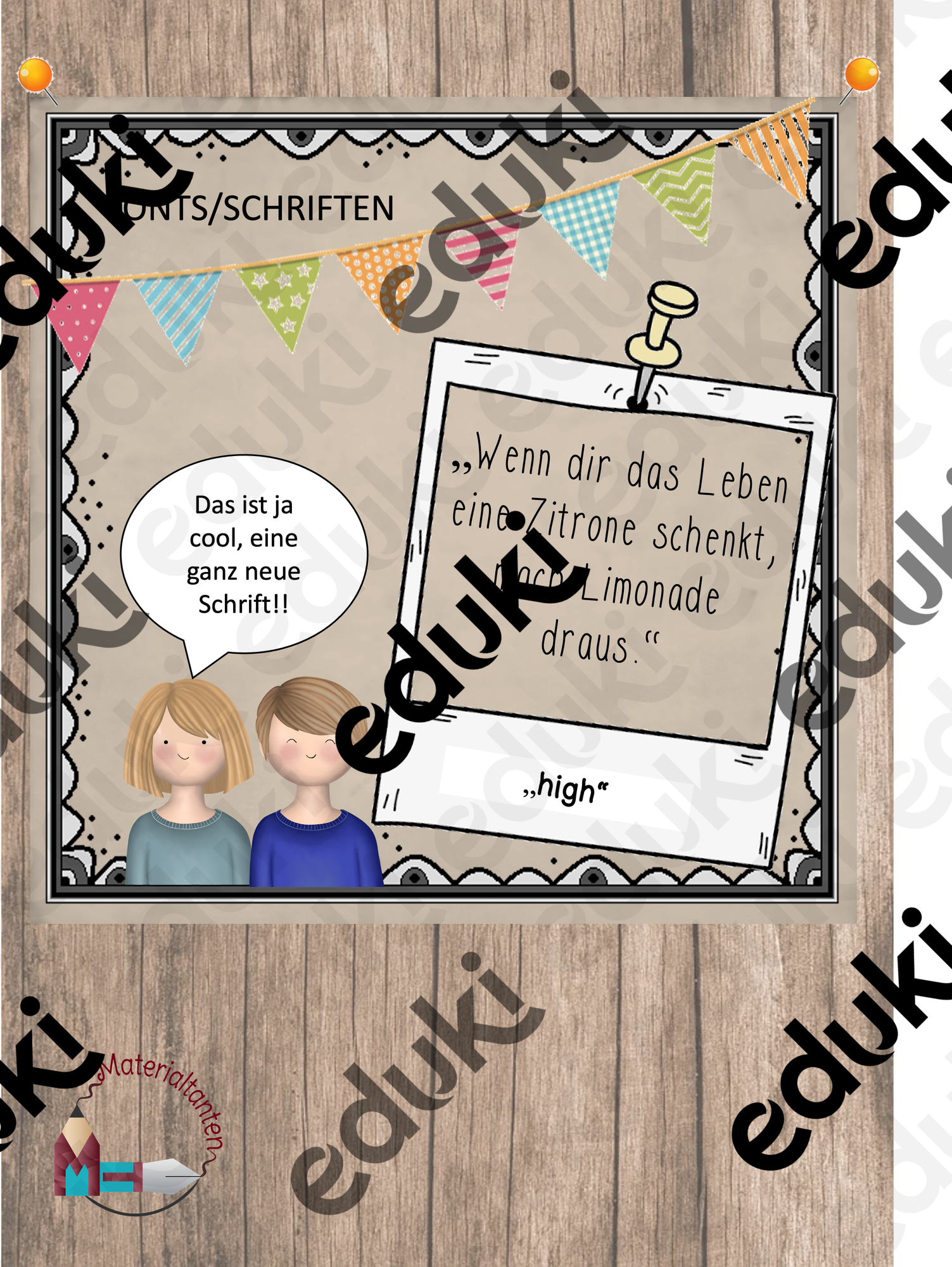
selbst erstellte Schriftarten - "high" - tolle Schrift/font für dein Unterrichtsmaterial - Materialtanten - Deckblatt
Einfach und bescheiden, etwas höher und daher etwas besser zu lesen. Klare Linien schaffen einen klaren Blick!
Mit dieser Schrift kannst du dein Unterrichtsmaterial ganz individuell gestalten!
"high" - tolle Schrift/font für dein Unterrichtsmaterial